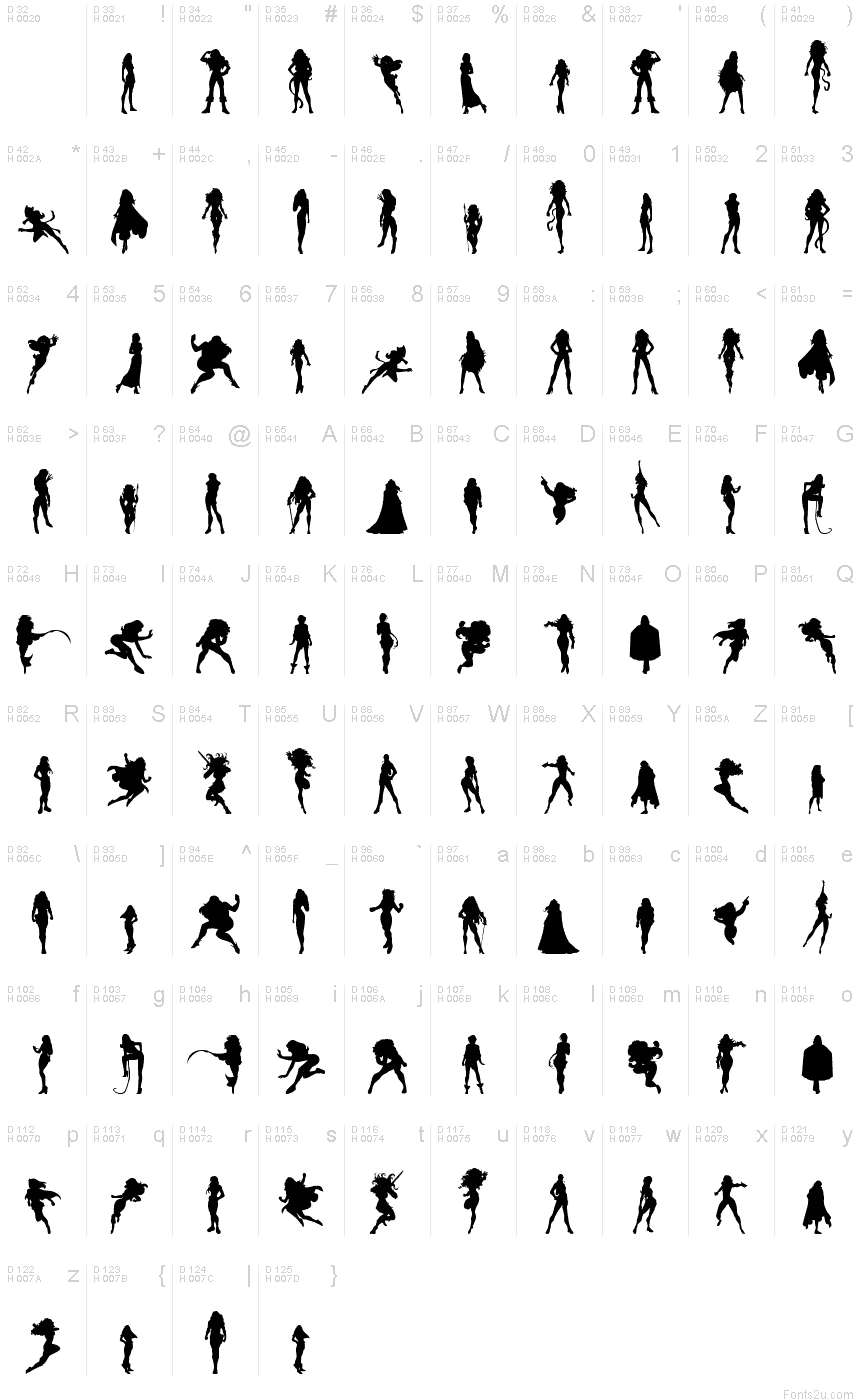
Action Women от Iconian Fonts — это бесплатный дингбат-шрифт с силуэтами супергероев, заряженный энергией комиксов. Фигуры с плащами, в динамичных позах и с развевающимися волосами придают набору живой графический импульс, который больше напоминает олдскульные боевики, чем обычные мультяшные иконки.
Шрифт отлично подходит для случаев, когда нужно быстро создать яркий акцент: будь то плакаты, обложки комиксов, приглашения, заголовки, мерч или скрапбукинг. Используйте этот бесплатный шрифт, когда вам нужно, чтобы одна фигура задавала тон всей композиции: эти формы считываются как полноценные силуэтные сцены, а не просто как мелкие декоративные символы.